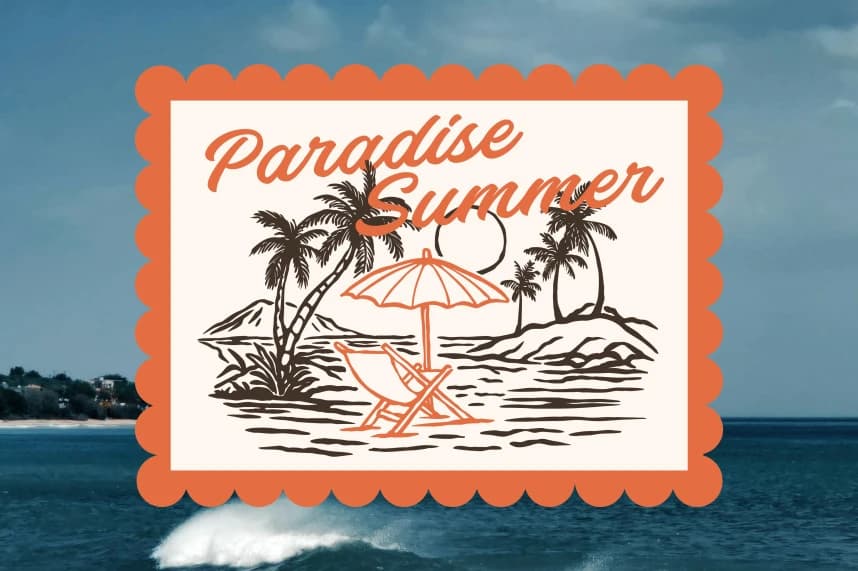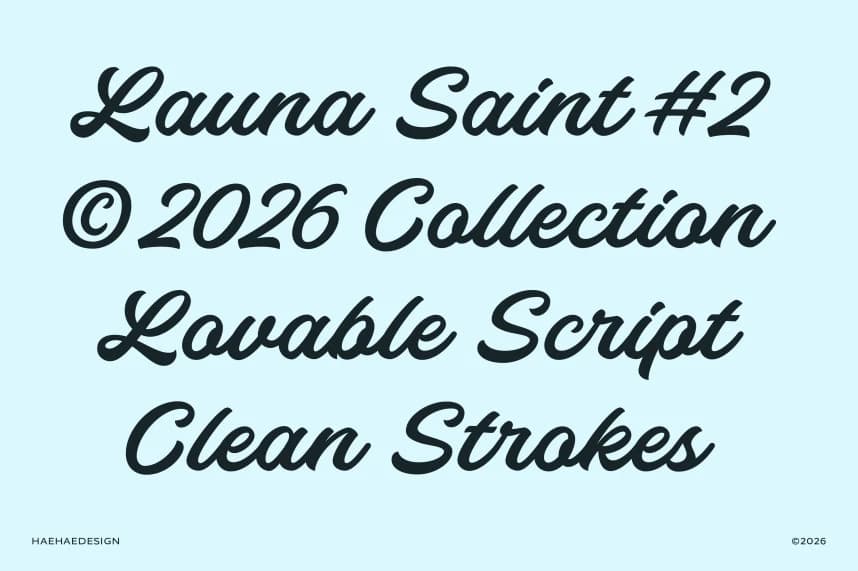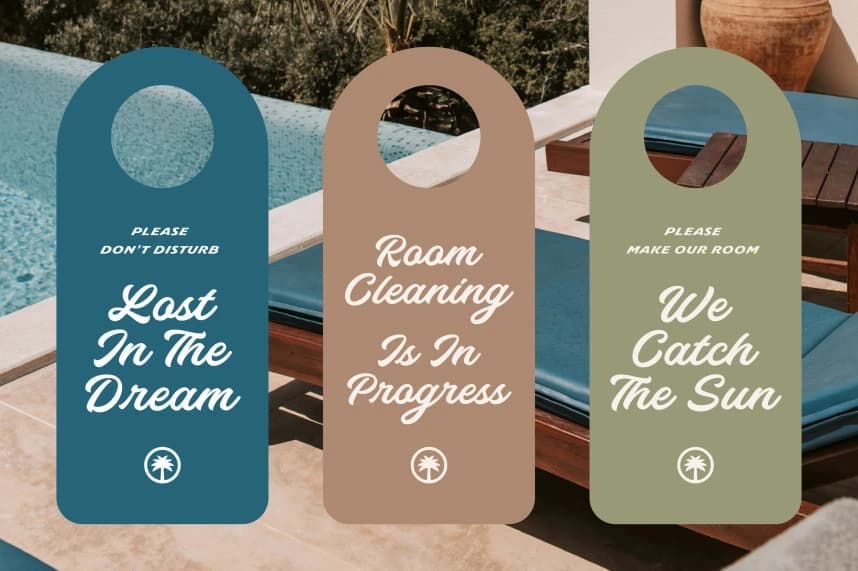
Launa Saint Font, esnek olacak şekilde tasarlandı; neşeyi ve zahmetsiz stili yansıtan sevgi dolu bir el yazısı fontudur. Bu yazı tipi temiz çizgilere sahip olup pürüzsüz, ritmik bir akış sunar ve modern fırça yazı stilinin cazibesini mükemmel şekilde yakalar.
Launa Saint Font esnek olacak şekilde tasarlanmıştır; neşe saçan ve zahmetsiz stil yayan sevimli bir kaligrafi yazı tipi. Bu tipografi temiz hatlar, pürüzsüz, ritmik bir akış sunar ve modern fırça yazımının çekiciliğini mükemmel bir şekilde yansıtır.